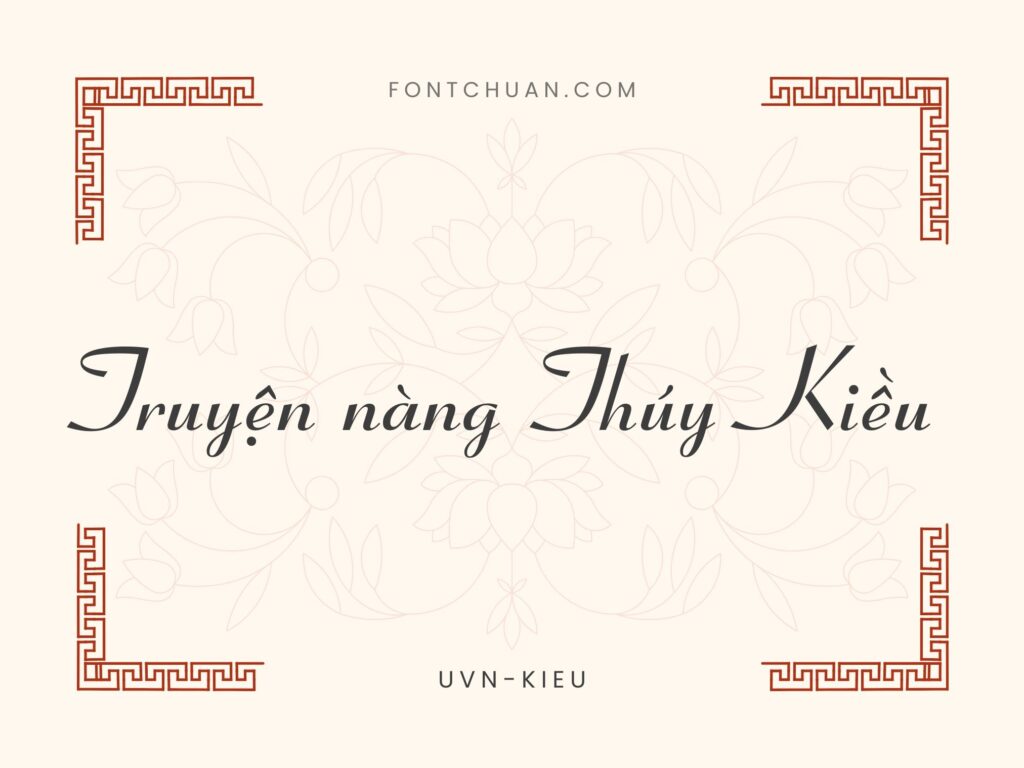
Font UVN Kieu Việt Hóa
UVN Kiều là một kiểu chữ thư pháp mang phong cách viết tay truyền thống, với các đường nét mềm mại và uyển chuyển, tạo cảm giác nghệ thuật và cổ điển. Font này chỉ được sưu tầm và đăng bởi thành viên của Font Chuẩn.
UVN Kiều có cấu trúc chữ với các nét thanh mảnh và độ nghiêng nhẹ, tạo nên sự duyên dáng và dễ đọc. Font này phù hợp cho các ứng dụng như thiết kế thiệp mời, tiêu đề, biển hiệu và các ấn phẩm in ấn yêu cầu sự trang nhã và nghệ thuật. Các ngành nghề như quảng cáo, giáo dục, công nghệ và bất động sản có thể tận dụng UVN Kiều để tạo điểm nhấn độc đáo trong thiết kế.